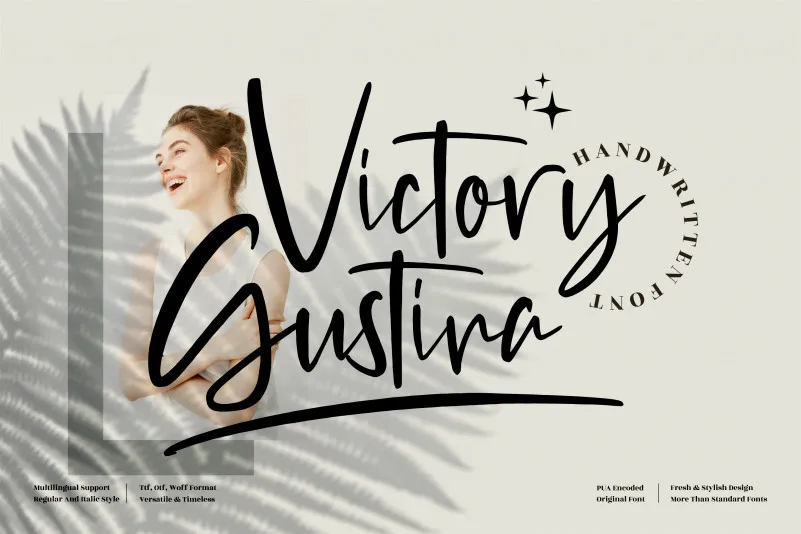
Victory Gustina Font – Download Grátis
Esta é uma fonte script delicada e encantadora que transmite elegância e classe. Foi especialmente projetada para aqueles que precisam de um aspecto agradável e renovador em suas criações. Com linhas suaves, este tipo digital oferece uma aparição única, perfeita para design gráfico requintado ou artesanato personalizado. Perspectype, o designer da fonte Victory Gustina Font, certamente manterá seu trabalho de arte sempre elegante e moderno com esta graciosidade tipográfica. Seja em cartões de visita profissionais, editoriais de estilo pessoal, ou até mesmo em artesanato de decoração, essa fonte oferece um toque único para qualquer projeto.